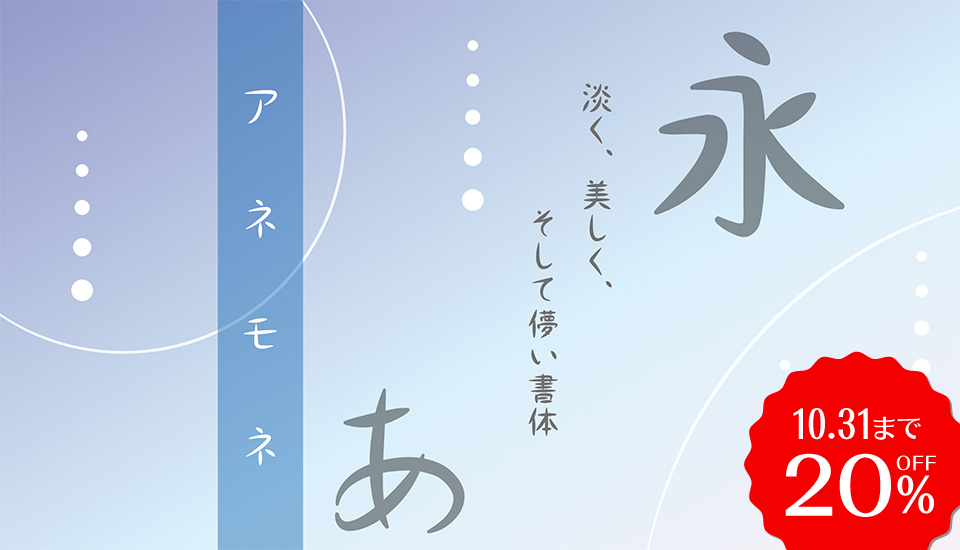
新登場アネモネ 淡く、美しく、そして儚い書体
モトヤの手書き風書体! 儚さをイメージした『アネモネ』
モトヤでは、「モトヤノート2B/4 (2018年)」に続き、2021年に手書き風書体の第二弾として「モトヤアネモネ1/3/5」を販売開始しました。アネモネの特徴やデザインのこだわりについてご紹介していきます。
モトヤアネモネとは
「モトヤアネモネ (以下、アネモネ)」はモトヤの手書き風書体です。モトヤでの手書き風書体の第一弾であった「モトヤノート」に続き「アネモネ」は手書き風書体の第二弾となります。
第一弾の「モトヤノート」が「温もり」や「優しさ」を表現したベーシックな手書き風書体だったのに対し、第二弾の「アネモネ」は手書き風書体に分類される書体としては異質な表情を持っています。
アネモネの表情は、どこか儚げで今にも消えてしまいそうな淡いイメージに仕上げられており、アネモネを使用することで、文面に悲しげで切ない感情を表現できます。
※ここでいう表情とは、その文字の持つ印象であったり、その文字で組まれた文章全体から感じ取ることができる雰囲気のようなものを指しています。
書体の特徴
手書き風書体には、手書きならではの人の温もりや優しさを感じさせる表情のもの、もしくはその文字を書いた人の人物像がぼんやりと想像できるものが多いと思います。
そんなポジティブな表情を持つ手書き風書体が多い中、アネモネは「淡くて儚い」という少々ネガティブな表情を持っています。
何故、ネガティブな表情を持たせたかというと、例えば恋愛ドラマや映画などでも場面の1つとして描かれる失恋シーンを想像してほしいのですが、そこには「儚くて切ない」「悲しい」表現の中に、その人が持つ純粋で綺麗な感情も表現されているかと思います。
そのネガティブの中にある綺麗なものを書体に落とし込めないかという思いから、手書き風書体にネガティブな表情を持たせてみようと開発されたのがこの『アネモネ』です。
書体名の由来
書体の特徴でも触れた「儚い」「失恋」などのキーワードから、「儚い恋」を花言葉に持つ『アネモネ』が案として挙がり、書体のイメージに合っていて音も綺麗だったことからそれが書体名に選ばれました。
ウェイト展開
アネモネは、細いものから太いものまでW1/3/5の3種類のウェイトで展開しており、文字が太くなるにつれて段々と涙で滲んだような表情になっていきます。
何故そう見えるかというと、文字の太め方にポイントがあるからです。それは始筆と終筆は細いままで、送筆のみを丸く太めていったというところです。これにより、まるで墨をたっぷり含んだ筆で書いた文字のような「滲み」で太さを表現しています。
W1/3/5では、始筆と終筆の太さに大きな違いはありません。
始筆と終筆の太さが変わらない分、ウェイトが大きくなるにつれて送筆の部分のみで文字全体の濃度を調整しないといけません。
これは画数が少ない文字であればそう問題にはなりませんが、画数が多い文字だと、濃度を稼ごうとしたときに送筆同士が接触してしまいます。
そのため、文字の形状や画数によって送筆の太める程度を調整し、横線・縦棒同士での接触を抑える作業が必要でした。ここが制作で一番苦労した部分です。
使用例
アネモネが持つ表情には、単に「儚い」「悲しい」というイメージだけではなく、先にも述べたように純粋で綺麗な感情や、涙のようなしっとりとした水気のある印象も持っているため、例えば化粧水のような保湿を目的とした商品のパッケージや、感情表現に使われるテレビテロップなどもそうですが、「読ませる」よりは「感じさせる」書体なので、メッセージ性のある媒体に適しています。
書体見本
モトヤアネモネ1/3/5 Std
モトヤEXアネモネ1/3/5